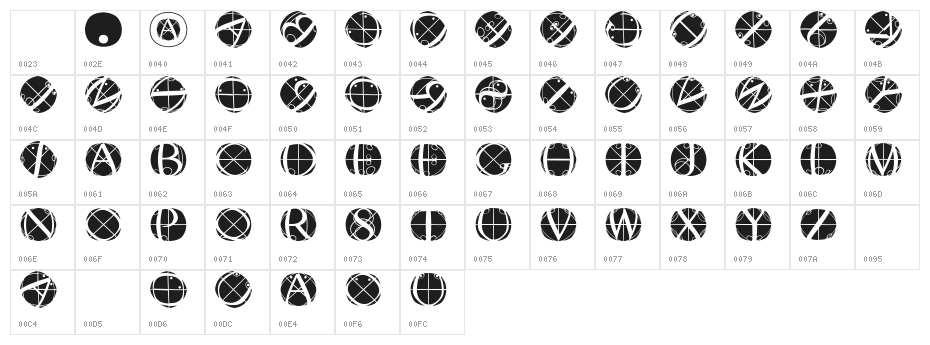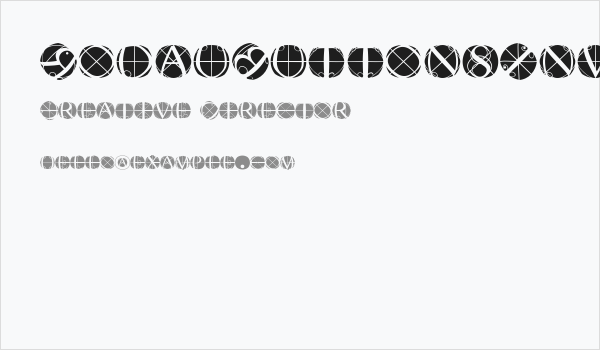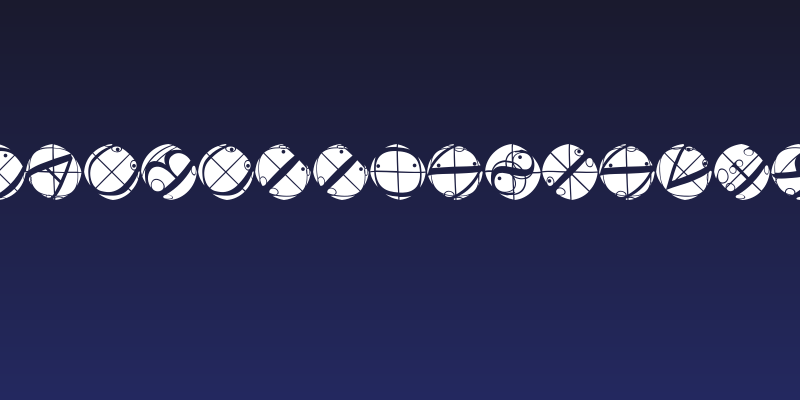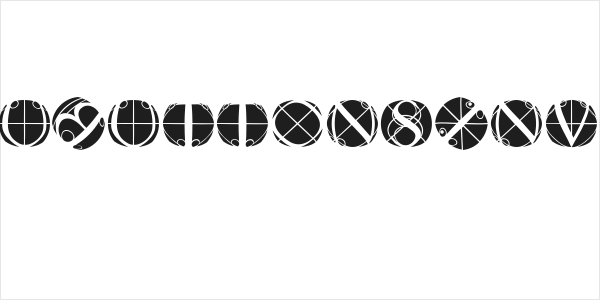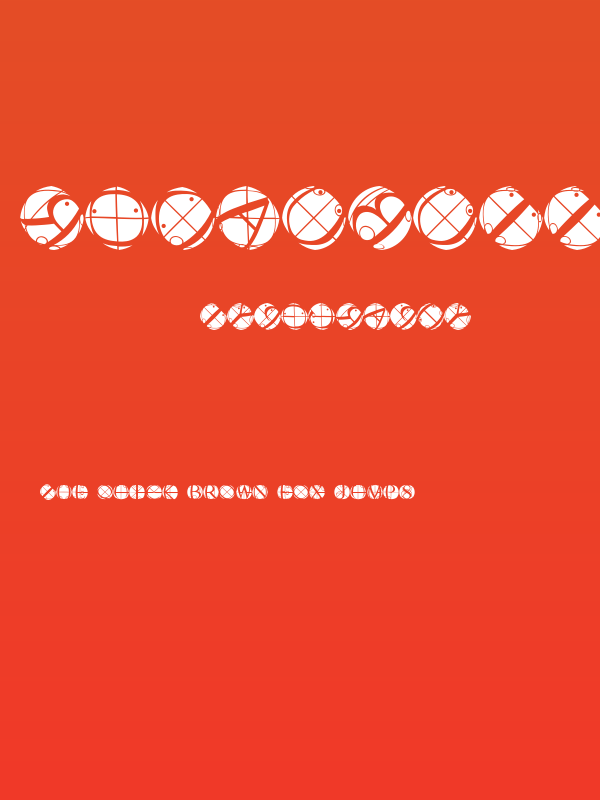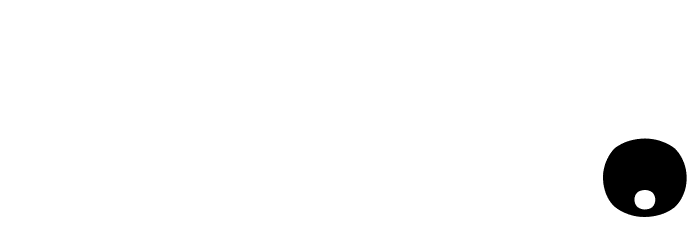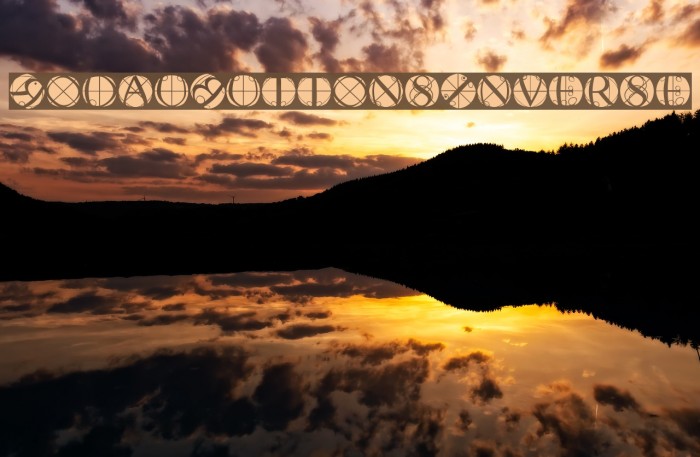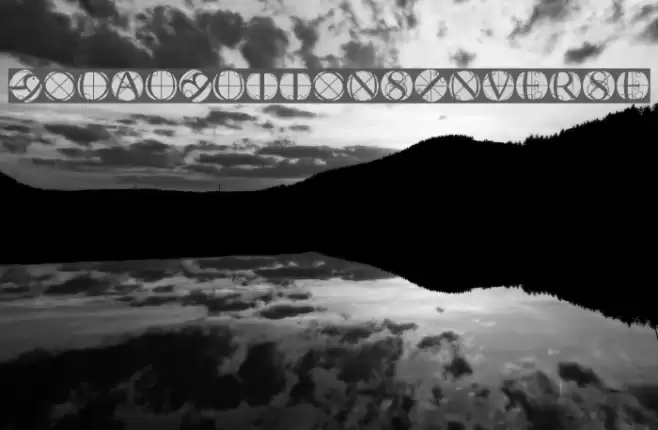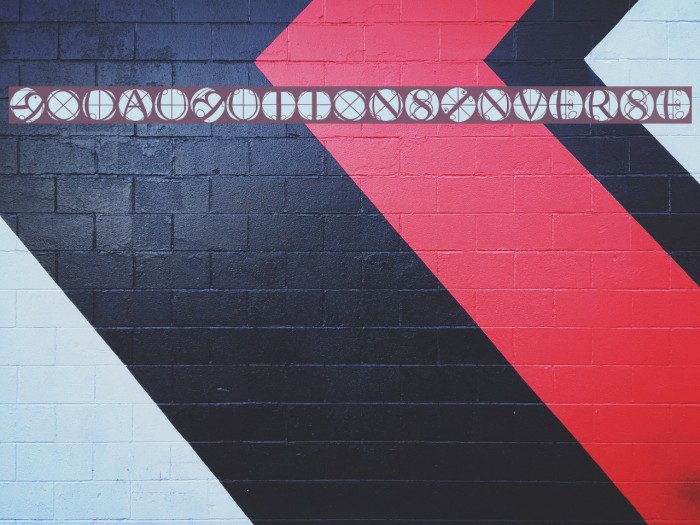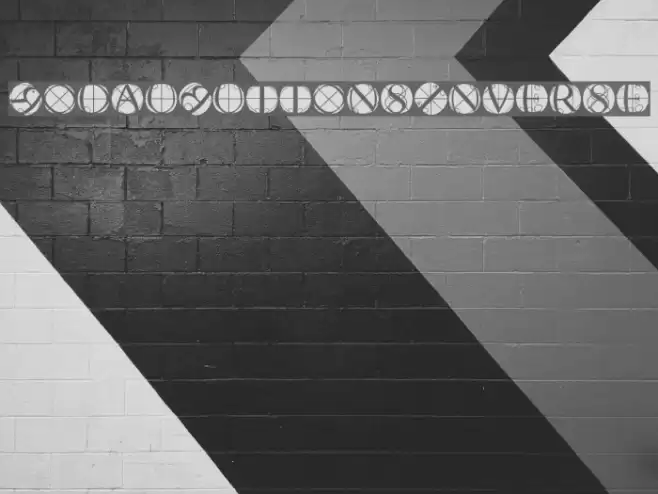
RodauButtonsInverse Font
| النمط العام | Modern, Futuristic |
| حالة الاستخدام | Logos, Posters, Artistic Designs |
| مشاريع مقترحة | Ideal for logo design, album covers, posters, and any project requiring a bold, artistic touch. |